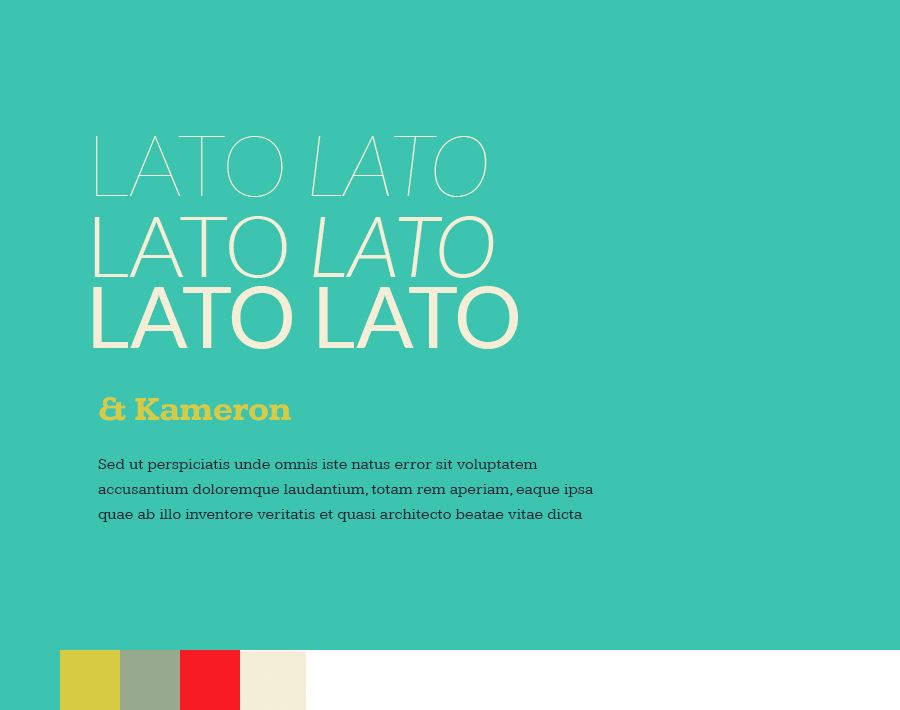
The Rise of Google Fonts
Я занимаюсь дизайном веб-сайтов WordPress с 2006 года. Пустое пространство и типографика — это два элемента, которые занимают большую часть моей одержимости, и когда все сделано правильно, накрывают стол для опьяняющего опыта.
Как человек, ответственный за создание цифровых продуктов, потребляемых массами, у меня есть только несколько вариантов упаковки шрифтов. Google Fonts бесплатны и имеют открытый исходный код, поэтому выбирать их удобно.
Исторически выбор шрифтов Google всегда казался посредственным. Roboto, Open Sans и Lato — одни из самых популярных и приличных, но они вездесущи, и мы видим их повсюду.
Расцвет Google Fonts
За последний год или около того все изменилось. Качество и уникальность новых шрифтов значительно возросли.
Google Fonts улучшил свою игру и теперь является жизнеспособным источником для выбора шрифта.
Вот три недавно выпущенных шрифта, которые я люблю и часто использую:
1. Шрифт Outfit
Outfit — красивый шрифт без засечек, вдохновленный богатым лигатурой геометрическим словесным знаком одежды. Он был разработан Родриго Фуэнзалида и находится в свободном доступе в Google Fonts.
Outfit — переменный шрифт
Outfit — это изменяемый шрифт, который дает пользователю свободу выбирать, насколько тяжелым должен быть шрифт.
Outfit — Образец текста
Outfit — великолепный шрифт для отображения запоминающихся цитат, как показано ниже. Тейлор Свифт говорит: «Я хочу, чтобы меня знали за хорошие вещи в моей жизни».
Outfit – Начертание шрифта
Outfit поставляется в следующих 9 вариантах насыщенности + переменная: Thin, ExtraLight, Light, Regular, Medium, SemiBold, Bold, ExtraBold, Black.
2. Inter Font
Inter — это семейство вариативных шрифтов, тщательно разработанных для экранов компьютеров.
Он был разработан Расмусом Андерссоном и находится в свободном доступе в Google Fonts.
Inter — переменный шрифт
Inter — это изменяемый шрифт, который дает пользователю свободу выбирать, насколько тяжелым должен быть шрифт.
Inter — Образец текста
Inter — великолепный шрифт для отображения запоминающихся цитат, как показано ниже. Тейлор Свифт говорит: «Я хочу, чтобы меня знали за хорошие вещи в моей жизни».
Inter – Насыщенность шрифта
Inter поставляется в следующих 9 насыщенностях + переменная: Thin, ExtraLight, Light, Regular, Medium, SemiBold, Bold, ExtraBold, Black.
3. Шрифт Figtree
Figtree — это чистый, но удобный геометрический шрифт без засечек для использования в веб-приложениях и мобильных приложениях. Он был разработан Эриком Кеннеди и находится в свободном доступе в Google Fonts.
Figtree — изменяемый шрифт
Figtree — изменяемый шрифт, который дает пользователю свободу выбирать, насколько тяжелым должен быть шрифт.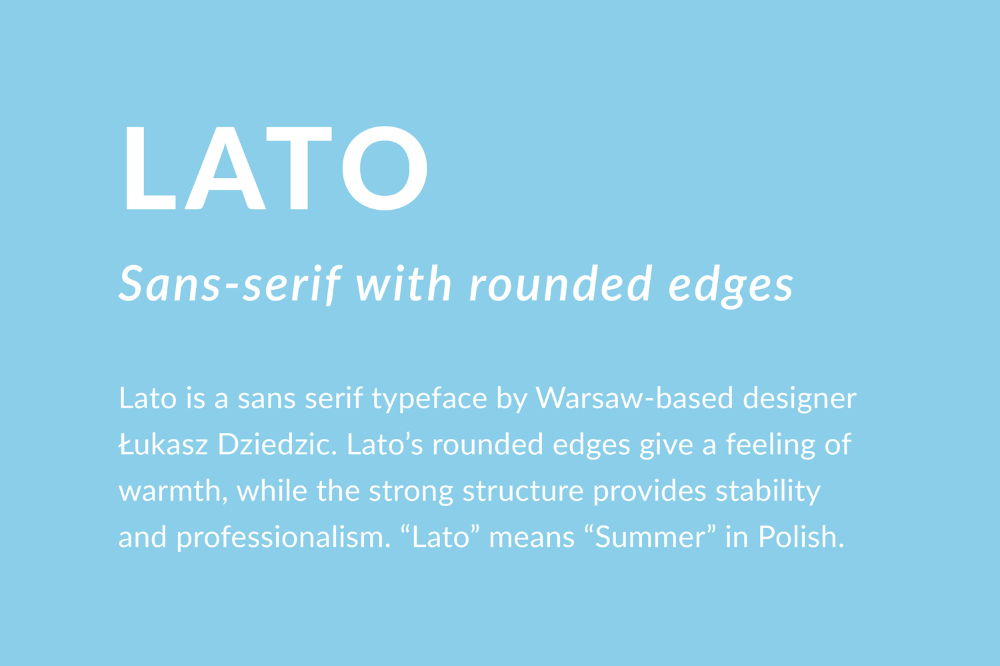
Figtree — Образец текста
Figtree — великолепный шрифт для отображения запоминающихся цитат, как показано ниже. Тейлор Свифт говорит: «Я хочу, чтобы меня знали за хорошие вещи в моей жизни».
Figtree – Толщина шрифта
Figtree поставляется в следующих 7 насыщенностях + переменная: Light, Regular, Medium, SemiBold, Bold, ExtraBold, Black.
Лучшие шрифты Google в 2020 году
Шрифты Google набирают популярность повсюду. Ими пользуются многие люди со всего мира. Они просты и бесплатны в использовании.
Они представляют вам красивые настройки и различные коллекции типографики. Эти шрифты разрабатываются разработчиками шрифтов и агентствами по всему миру. Сейчас их более 915 шрифтов.
Вы можете пользоваться ими как для личного, так и для коммерческого использования.
Давайте откроем для себя лучшие шрифты 2020 года ниже.
Он самый любимый среди других. Набрав около 6,3 триллионов просмотров, этот шрифт невероятен. Вы можете применить это для различных приложений.
Шрифты предоставляют вам 12 стилей, которые имеют механический скелет и геометрическую форму. Он предлагает вам удобные функции и открытые кривые. Вы можете сделать ритм чтения более естественным, используя этот шрифт.
Этот шрифт является вторым по популярности. Он имеет шрифт гуманистического гротеска. Он предлагает вам 10 стилей, которые на сегодняшний день просмотрены 5,6 триллионов раз.
Пользователи оптимизируют использование для различных интерфейсов, таких как мобильный телефон, печать и веб-сайт. Вы можете испытать наилучшие характеристики разборчивости в каждой буквенной форме. Кроме того, вы можете увидеть дизайн с открытыми формами, вертикальным напряжением и дружелюбным внешним видом.
Шрифт Lato занял третье место среди любимых шрифтов. Его шрифт без засечек. Просмотр увеличился до 16 %, что набирает 434 миллиарда просмотров.
Фигура загружена более 633 миллиардов раз. Более того, к 2020 году он увеличится на 14%. Вы можете испытать его 12 потрясающих стилей для своих проектов.
МонтсерратВ последнее время это один из самых быстрорастущих шрифтов. Многие пользователи также применяют этот шрифт, будь то для офлайн- или онлайн-проекта. Его простая форма делает его простым.
Со временем этот шрифт набирает популярность из-за огромного количества скачиваний. Он увеличивается на 40 % и достигает 591 миллиарда просмотров. Он получает лучший рейтинг среди самых привлекательных шрифтов.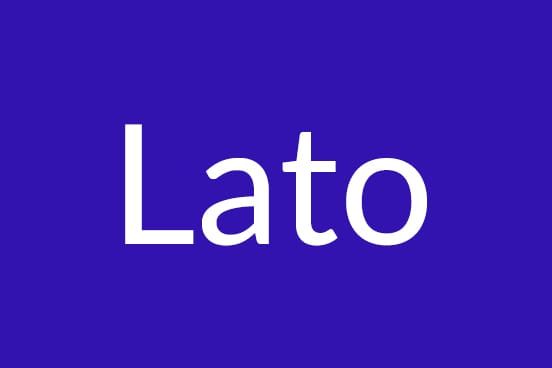